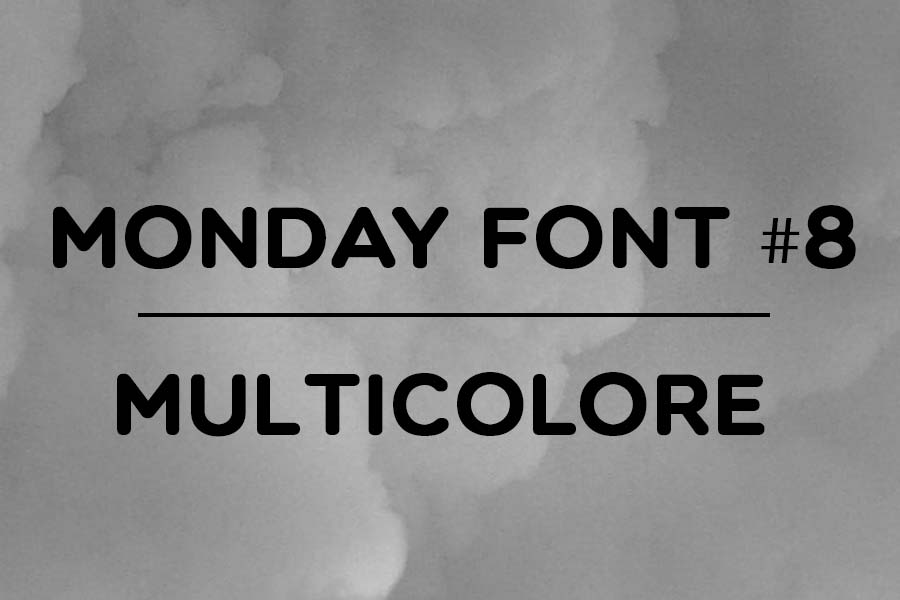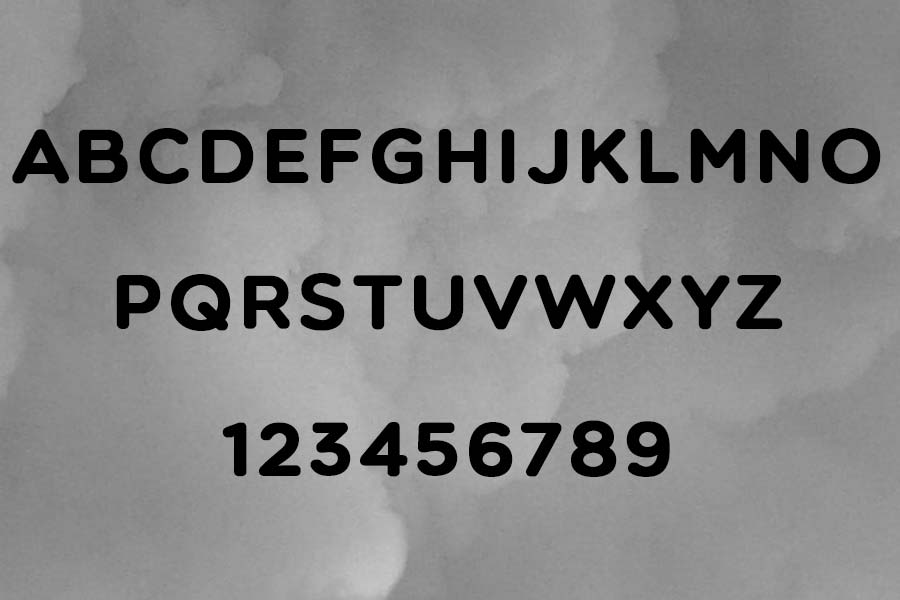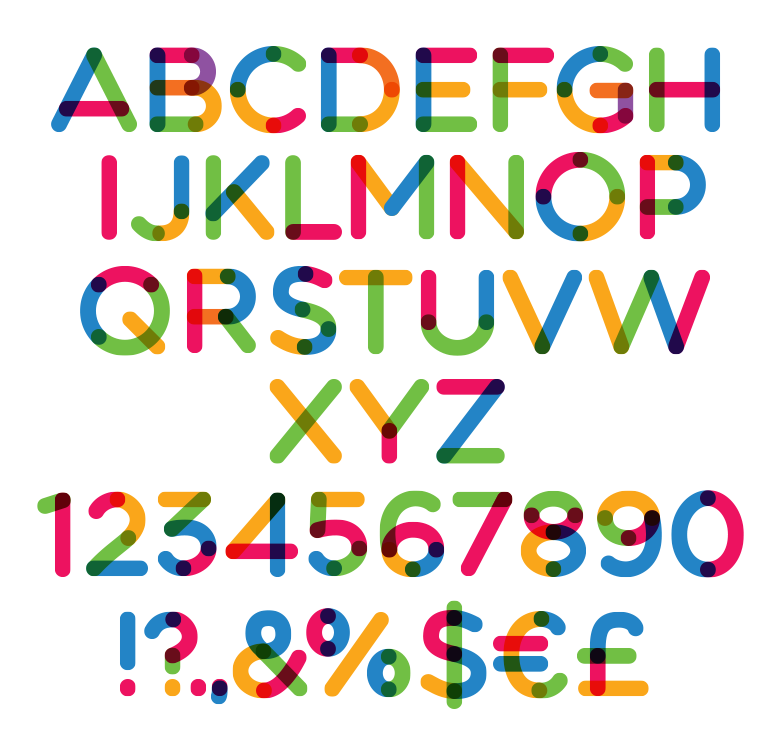
Otro lunes más volvemos con nuestra particular recopilación de fuentes gratuitas en el especial Monday font. Hoy le toca el turno a otra tipografía sans serif bajo el nombre Multicolore. Bonita y redonda. Gracias a Ivan Filipov